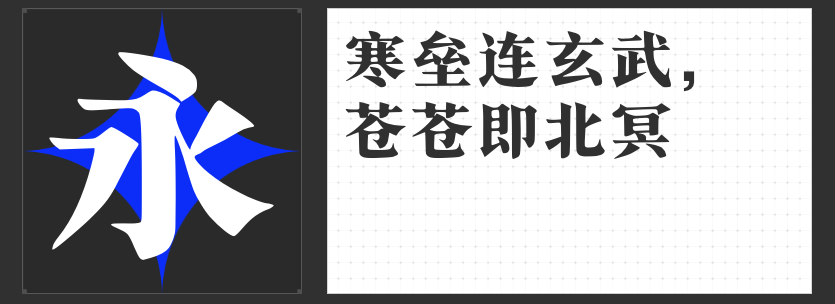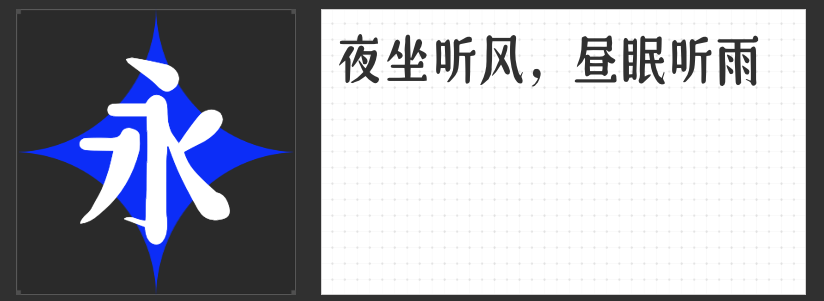
四款宋体佳作推荐:传统韵味与现代美学的完美交融
在字体设计的广阔天地中,宋体以其独特的横细竖粗结构与精致的衬线装饰,始终占据着重要地位。本文将为您推荐四款各具特色的宋体佳作,它们不仅传承了宋体的经典韵味,更在设计细节中融入了创新元素,成为设计师们不可多得的创意利器。
一、励字大标宋简繁
这款字体巧妙融合了老宋体的刚劲与黑体的现代感,横轻竖重,字脚处以锐利的三角装饰收尾,点、撇、捺等笔画尖端尽显力度,整体字形端正而不失清秀,适用于需要展现权威与雅致的场合。
以手写风格为基底,高手庆科自由宋 大宋在保持宋体横细竖粗的传统基础上,赋予了字体圆润流畅的线条与灵动的装饰角。横画末端的圆形点缀,钩笔的细长上挑,让每一字都洋溢着趣味性与生命力。其西文部分同样采用圆润设计,与中文风格和谐统一,适合追求轻松愉悦氛围的设计项目。
三、高手兵克高雅宋
高手兵克高雅宋以其修长的字形与精致的笔画处理脱颖而出。转折处的尖角设计,赋予字体优雅气质;竖笔收尾的向左切口,则增添了几分独特韵味。这款字体适合用于需要展现高雅、精致感的品牌标识或广告文案中。
四、机甲宋玄武号
作为宋体与机甲元素的跨界融合,机甲宋玄武号以其修长的字形与刚柔并济的笔画设计,创造出前所未有的视觉冲击力。它既保留了书法的韵律美,又融入了机甲的科技感,是科幻题材或未来风格设计中的理想选择。
这四款宋体字体,每一款都是对传统与现代的深刻诠释,它们以各自独有的方式,为设计作品增添了无限魅力与深度。